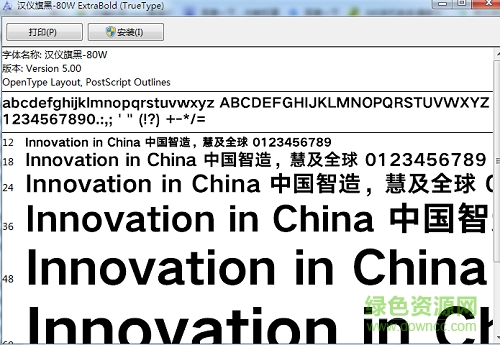
hyqihei hzw又稱漢儀旗黑80w,字體字型非常大氣,字體端正大方,看起來古樸厚實(shí),適用于廣告設(shè)計(jì)、平面設(shè)計(jì)等場(chǎng)合,有需要的朋友歡迎來綠色資源網(wǎng)下載使用!
hyqihei hzw是一款比較不錯(cuò)的字體,它具有不錯(cuò)的字體筆鋒,讓人感覺部分娟秀,同時(shí)能夠運(yùn)用到眾多設(shè)計(jì)當(dāng)中如藝術(shù)字設(shè)計(jì),海報(bào)設(shè)計(jì)等,能夠發(fā)揮出不錯(cuò)的顯示效果!